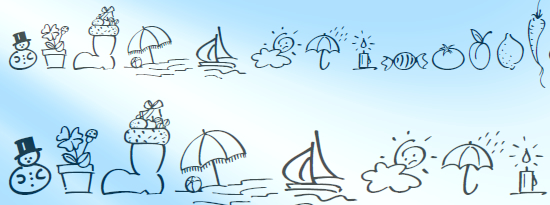
30 tipografías útiles de estilo dingbats
Como ya he mencionado en alguna ocasión, los dingbats (o tipos de letras de símbolos) son tipografías normales y corrientes, pero tienen una particularidad, en lugar de letras contienen símbolos, son también conocidos como pictogramas. Son ficheros de de tipos de letras (Truetype o Type 1), que en lugar de tener asignados caracteres alfabéticos o numéricos contienen dibujos monocromos, generalmente en blanco y negro.
Los dingbats a veces pueden ser una forma muy útil de obtener un gráfico de una manera sencilla. Estos dibujos se utilizan como cualquier tipo de letra, pudiendo modificarse sus atributos como si se tratara de un texto normal (tamaño, alineación, color, etc.). También pueden ser convertidos en trazos en un programa de ilustración, lo que permite tratamientos más avanzados. Por ejemplo los simbolos, los caracteres ornamentales en la composición, los objetos pueden ser muy útiles en el diseño, ya que son similares a la forma o conjuntos de iconos que vienen como tipos de letras.
Además, con la propiedad @font-face de CSS3, donde se hace posible utilizar cualquier tipo de letra en páginas web, es bastante seguro de que con los dingbats encontrarás una zona en tus diseños para su uso.
En el artículo Designing With Fonts: 30 Useful & Free Dingbats, de WebResourcesDepot, nos proporcionan unos 30 conjuntos gratuitos de tipos de letras dingbats de calidad, para ampliar nuestra colección de tipografías. La temática de los dingbats es tan variada como uno se pueda imaginar, y cubren casi todas las necesidades gráficas. Encontramos material figurativo realista, símbolos estilizados, signos, formas geométricas... algunos tienen una aplicación muy limitada, otros más general. Existen también algunos dingbats que sirven especialmente para crear fondos de tramado continuo, a modo de mosaico.
¿Qué ventaja tiene emplear estos dingbats en lugar de clipart convencional? En especial, el hecho de que para usar un dingbat no hace falta ningún programa especial. Se pueden utilizar desde cualquier programa de Windows o Mac, y sin problemas de versiones. La limitación principal que tienen es que son monocromos, pero se pueden colorear fácilmente.